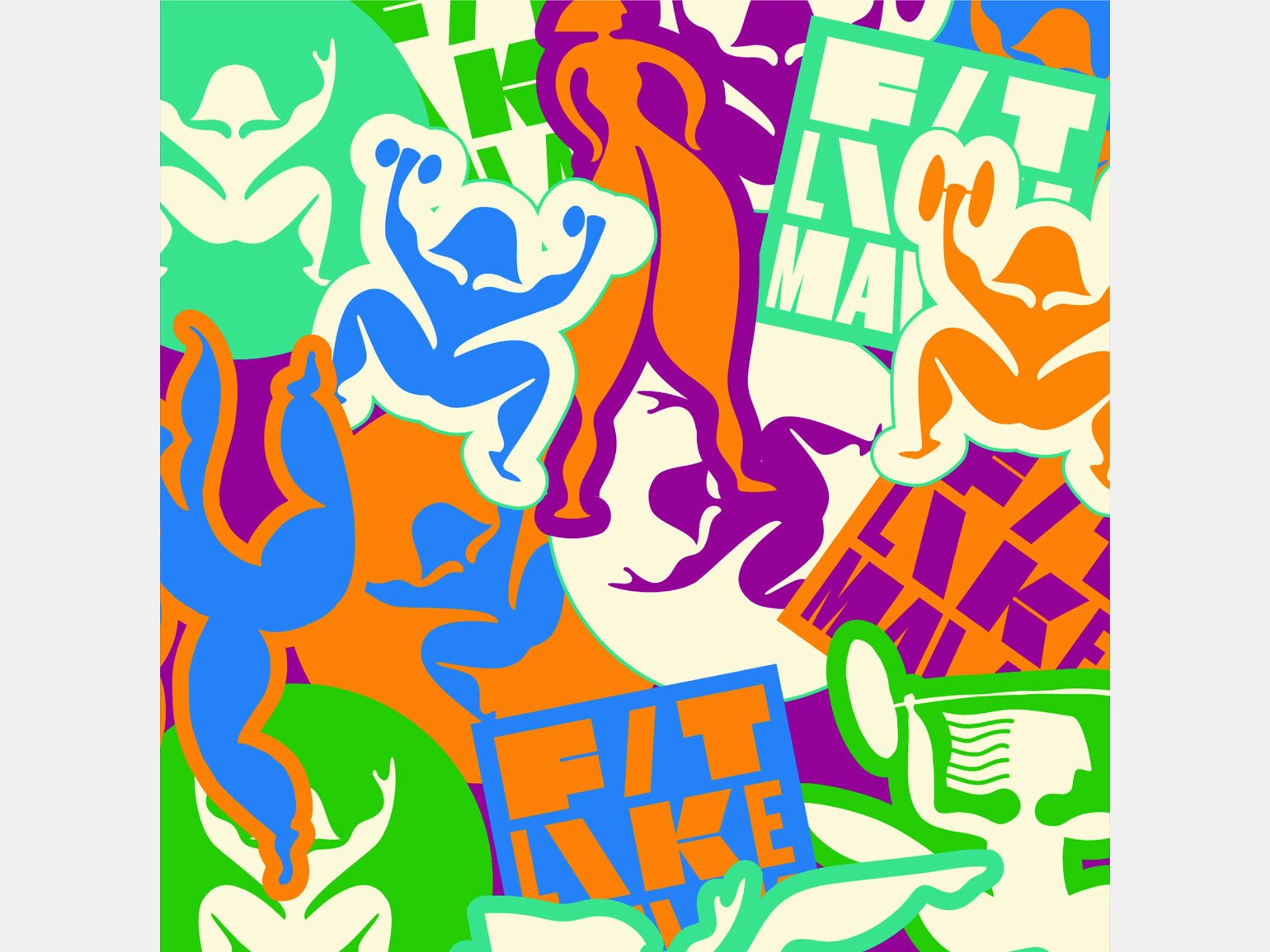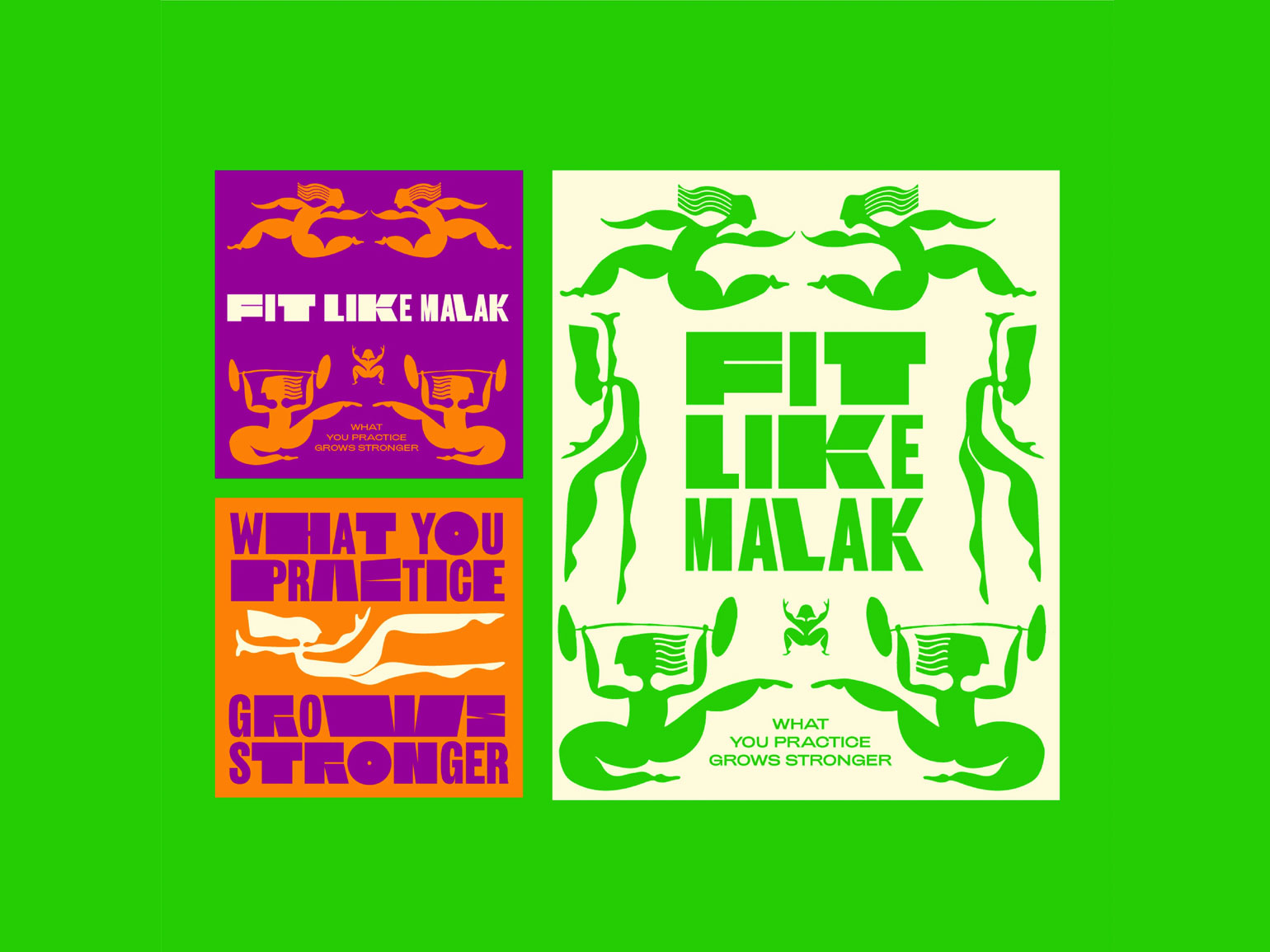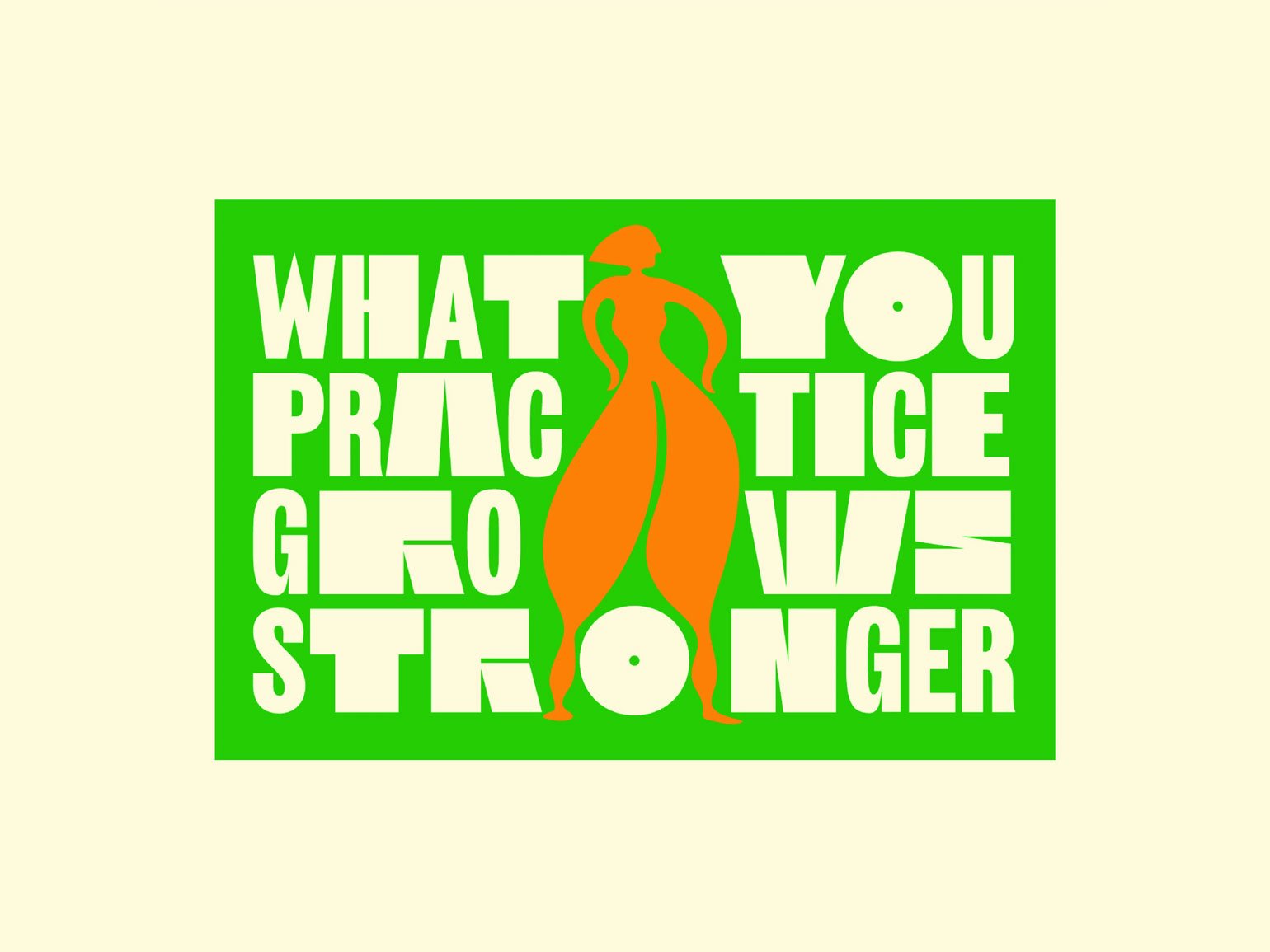
Графический дизайнер из Каира вдохновился фигурами спортсменов, чтобы создать шрифт
А логотип-иконку срисовал с заказчицы.
Фитнес-инфлюенсерка из Египта Малак Эль Аюти запустила программу Fit Like Malak и пригласила оформить её дизайнера из Каира Омара Мобарека. «Большинство моих проектов начинаются с черновых эскизов ручкой на бумаге, потому что это естественно для меня и даёт гораздо больше возможностей для мыслей и идей, — говорит Омар. — Это очень хорошо подошло для этого проекта. Малак рассказала мне, что она работает с любым типом телосложения и разрабатывает программу, подходящую для каждого человека. Было важно это уловить».
Дизайнер нарисовал множество динамичных эскизов и наконец получил результат, к которому стремился. «Буквы широкие, тонкие, растянутые и сжатые, отражающие всё разнообразие типов фигур».
Омар включил в брендинг любимое упражнение блогерки — приседание. Дизайнер нарисовал фигурку, выполняющую его, в форме буквы М. «Позже мы обнаружили в её ленте фотографию, которая выглядела точно так же, как иконка, это было приятно», — говорит он.
А любимые элементы Омара — абсурдные. Например, фигурка девушки, которая поднимает штангу с гирями в положении растяжки. А другая делает стойку на одной руке. «У нее непропорциональное тело, одна нога больше другой, но в ней есть визуальный баланс, который делает это осмысленным», — объясняет он.
Иконки срисованы с фигуры самой атлетки. «Я хотел, чтобы она сказала: „Это я“», — говорит Мобарек.